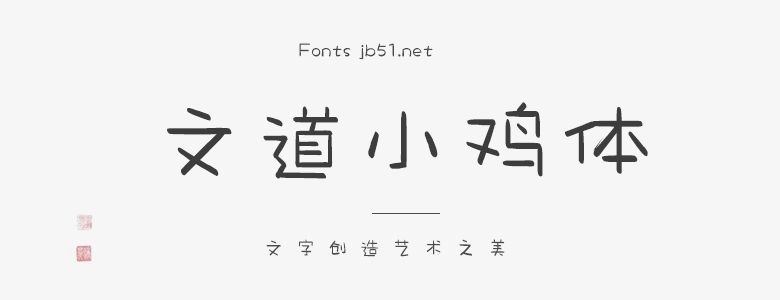
文道小雞體是一種極具特色的書法字體,它將傳統(tǒng)書法的韻味與現(xiàn)代設(shè)計(jì)元素巧妙地融合在一起。這款字體的設(shè)計(jì)靈感源于中國(guó)傳統(tǒng)書法,同時(shí)又兼具現(xiàn)代感與時(shí)尚氣息。 文道小雞體的特點(diǎn)在于其獨(dú)特的筆觸和線條,它們粗細(xì)有度,富有節(jié)奏感。每個(gè)字形都經(jīng)過精心設(shè)計(jì),以保持整體字體的和諧與美感。其字體結(jié)構(gòu)寬松,給人以舒適自然的感覺。此外,該字體還具有良好的識(shí)別度,適合在各種場(chǎng)合下使用。 在細(xì)節(jié)處理上,文道小雞體表現(xiàn)出色。字體中的曲線部分流暢自然,轉(zhuǎn)折處則保留了一定的頓挫感。此外,字體的筆觸交錯(cuò)有致,形成一種獨(dú)特的視覺效果。這些細(xì)節(jié)特征都使得文道小雞體在視覺上更加豐富、生動(dòng)。 總體來說,文道小雞體是一款兼具傳統(tǒng)韻味與現(xiàn)代感的書法字體,適用于各種文本設(shè)計(jì)場(chǎng)合。無論是海報(bào)、廣告、書籍還是包裝設(shè)計(jì),文道小雞體都能為作品增添一抹獨(dú)特的魅力和視覺亮點(diǎn)。